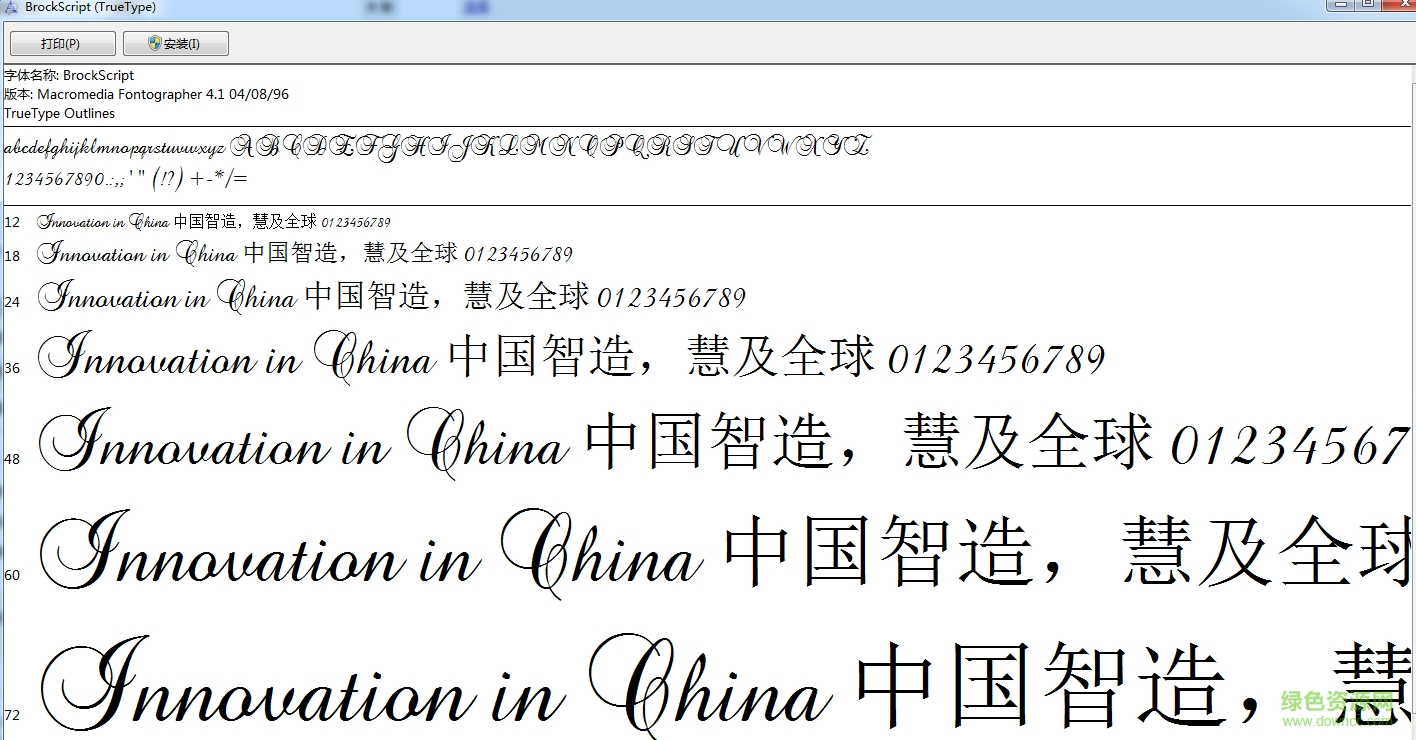
brockscript字體
brockscript字體是一款十分精美英文手寫(xiě)體,該字體筆劃連綿富于變化,起筆輕盈,轉(zhuǎn)折精巧,裝飾效果十分好,喜歡這款字體的朋友趕緊下載收藏吧!
brockscript
花體字體要求
花體字母是有一定的斜度的,整齊的排版也是很重要的因素,字母的長(zhǎng)寬比例更是有嚴(yán)格的要求,屬于基礎(chǔ)。
由于不是方塊文字而是字母文字,在文字整體造型的豐富性、多變性、靈活性和書(shū)家的自由性方面遠(yuǎn)小于我們的傳統(tǒng)中文書(shū)法,所以要達(dá)到視覺(jué)的美學(xué)效果及作品的多樣性,guideline起著關(guān)鍵的作用。